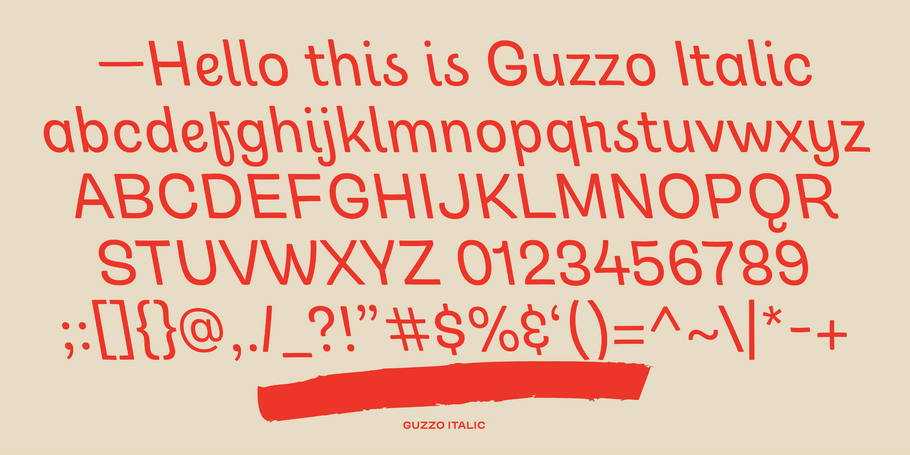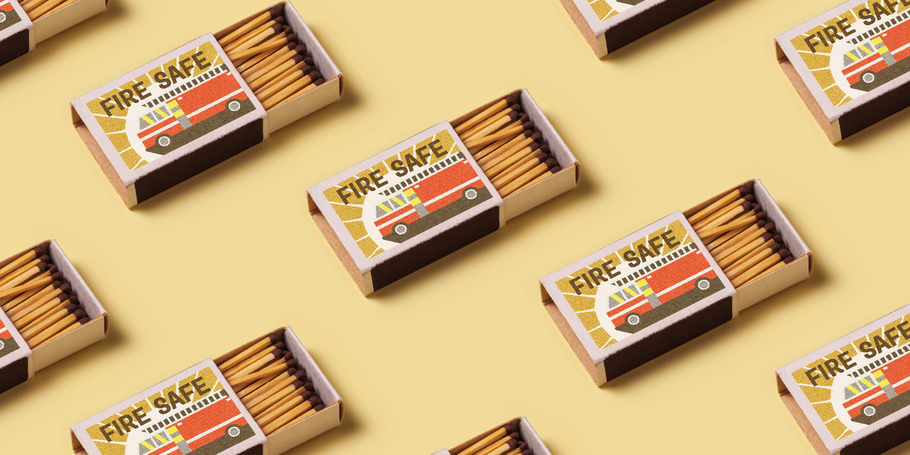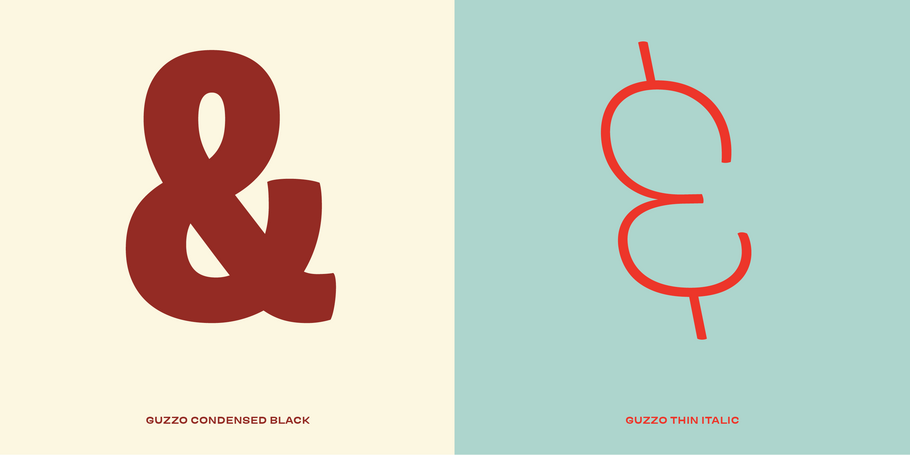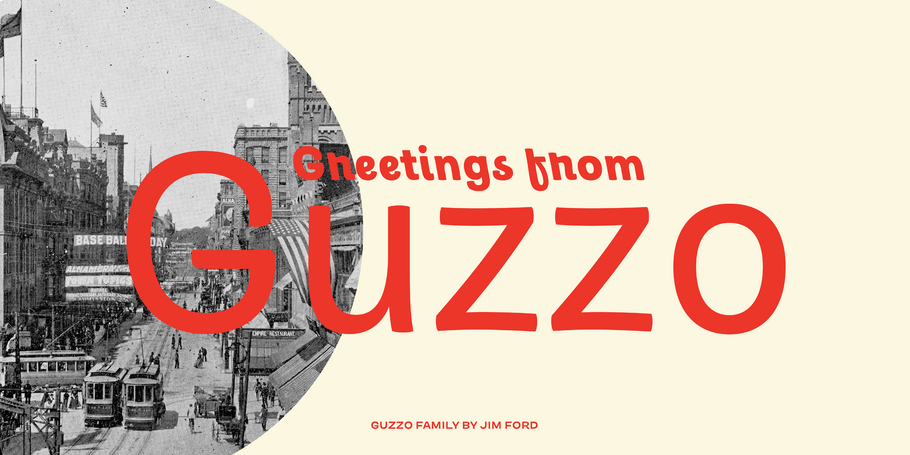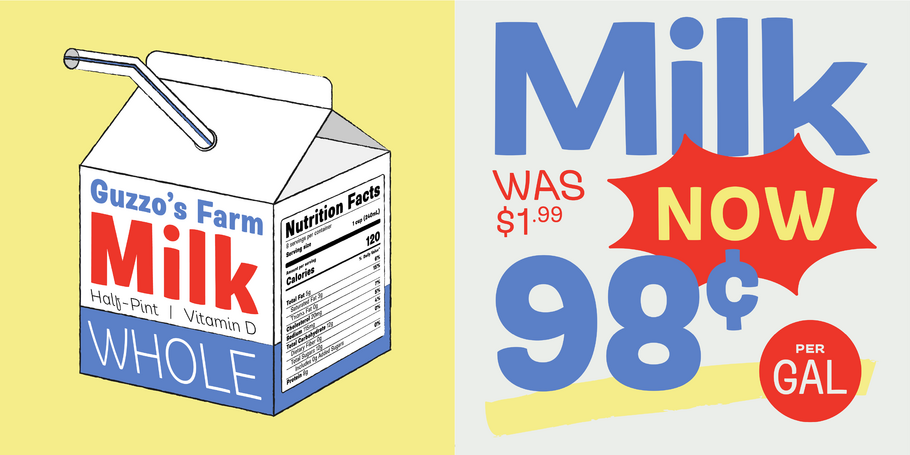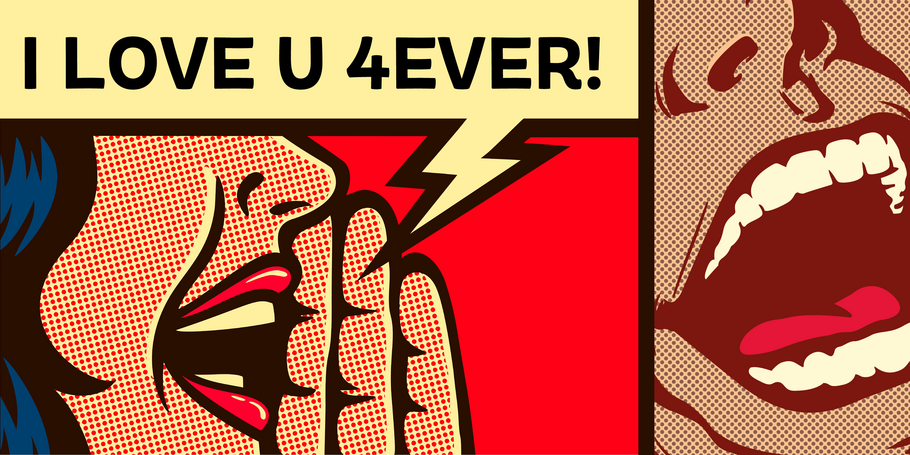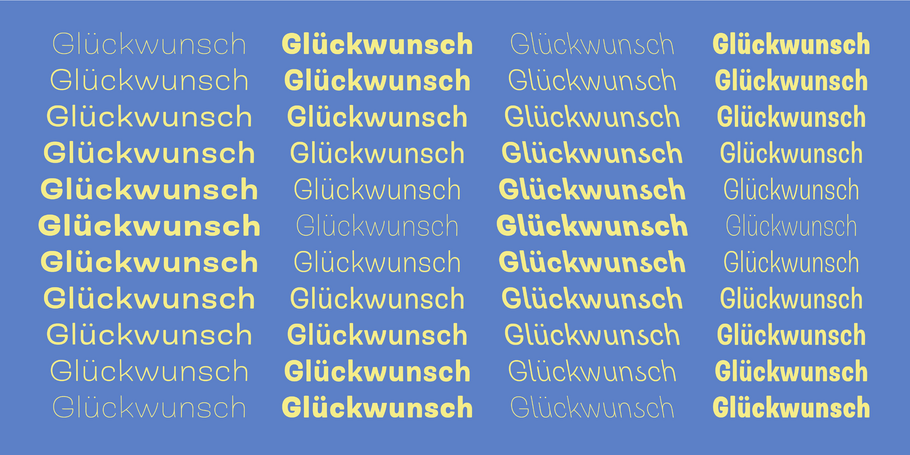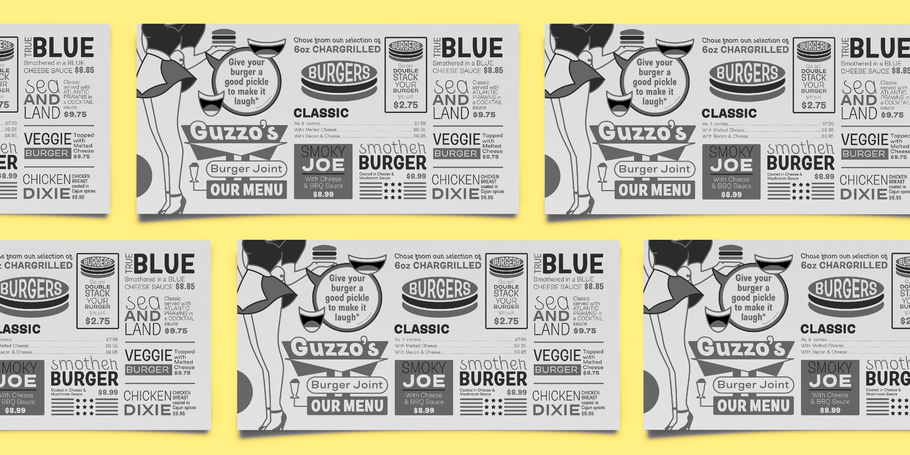
Guzzo
Die humoristische Sans.
Guzzo ist die spielerische Interpretation einer Grotesk aus der Mitte des 20. Jahrhunderts und ein frischer Beitrag zur Monotype Library. Auf den ersten Blick leicht exzentrisch und voller Überraschungen, überzeugt sie bei näherem Hinsehen mit einem unverwechselbaren Charme, der auf Details basiert, die Pinselschriften und der Kalligrafie entlehnt sind.
Das wahre Geheimnis dieser authentisch-nostalgischen Schrift ist das, was man aus ihr macht.
Mit einer enormen Palette an Strichstärken und Stilen meistert diese Familie jede Designaufgabe, seien es endlose Headlines oder dichte Textblöcke, gesetzt aus Guzzo Condesed, bis hin zur experimentellen Typografie in kleinen Punktgrößen, Etiketten oder Verpackungen mit Guzzo Extended. Der Charme der Familie entspringt den wunderbar verspielten Glyphen, sowohl in den geraden Schnitten als auch in der außergewöhnlich lässigen, nach links geneigten Kursiven. Mit der riesigen Auswahl alternativer Stilsets liegt es hauptsächlich in der Fantasie ihrer Benutzer … was sie aus der Guzzo-Familie herausholen und in welche Richtung sie ihr Design lenken.
Guzzo ist eine Frohnatur, mit einer warmen, bescheidenen und malerischen Qualität, die sie auf den ersten Blick gar nicht als digitale Schrift erkennen lässt. Sie kann ohne weiteres als „handgeschrieben“ durchgehen. Die Schrift harmoniert hervorragend mit Script- und Slab-Serif-Fonts und läuft bei Spielzeugen, Verpackungen, Speisekarten, TV-Titeln, Cartoons und im Merchandising zu Hochform auf. Guzzo ermutigt zu einer humorvollen Gestaltung und ist für Designerinnen und Designer geeignet, die an ihrem Computer „Handgemachtes“ entwickeln.
Die Schrift ist nach dem US-Maler Jeremy Pinc benannt, auch bekannt als Guzzo Pinc, und spiegelt die schrulligen, lustigen und pointierten Qualitäten seiner Gemälde wider: mit amorphen Figuren, geometrischen Formen und leuchtenden Farben.
Das wahre Geheimnis der authentisch-nostalgischen Guzzo-Familie ist das, was man aus ihr macht.